7 种最过度使用的字体以及从不使用它们的原因
已发表: 2019-09-13当您从事任何设计项目时,您都希望与众不同。 这涉及到所有工作方面——调色板、字体、整体语气——真的。
为了向您的观众提供令人惊叹的效果,您需要加入惊喜元素。 如果您使用与其他人相同的方法——常见的颜色模式、相似的结构,当然还有好的旧字体,这将很难做到。
如何确定哪些字体是常见的?
为确保您不会成为重复的受害者,请进行研究,看看您的创造性选择实际上是多余的可能性有多大。 当然,每个脏都有不同的规律——时尚品牌更喜欢细字母,而儿童品牌则选择卡通风格。
尽管如此,某些字体的使用量还是比其他字体多得多。 通过避免这些常见的选择,您可以使您的作品更具创意并牢牢记住读者。 我们列出了最常用的字体——所以现在您可以尽最大努力避免使用它们。
1. Helvetica / Helvetica Neue
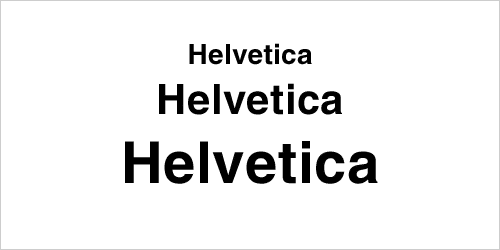
如今,认出 Helvetica 并不需要天才——它无处不在。 平面设计被专业人士和业余设计人员使用——主要是后者。 因为 Helvetica 在个人项目中如此普遍,所以它的声誉略有下降。
您可以将 Helvetica 用于低调的场合(例如演示标题),但如果我们谈论的是徽标或商品,最好选择具有个性的东西。 最重要的是,Helvetica 存在一些间距问题——字母几乎并排放置,这使得视力较弱的人难以阅读。
2. 图拉真
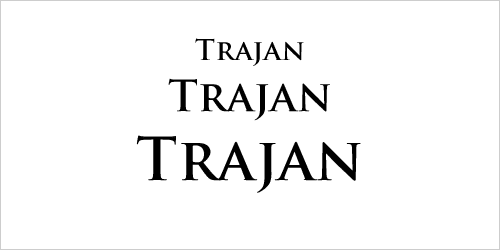
该字体深受好莱坞设计师和插画家的喜爱。 您可能已经在海报或邀请函上看到过它。 它还出现在教育和宗教材料中,部分原因在于其略微奇特的外观。
避免这个的原因之一是它的年龄。 它于 1989 年设计,是最早的专业字体之一,由 Adobe 设计。 该字体的灵感来自罗马建筑,使其非常适合官方场合。
这里还有另一个问题。 在线内容日新月异。 几年前,谷歌和BBC将他们的标志重新设计为简单的无衬线字体。 使用官方字体不再流行——除非场合需要。
3. 加拉蒙德
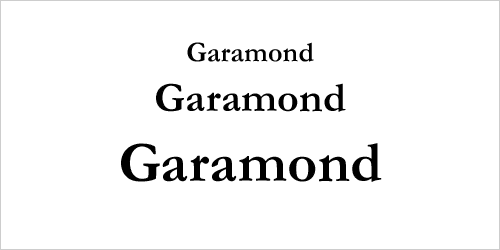
作为最多样化的字体之一,Garamond 产生了多种变体,这极大地解释了它的受欢迎程度。 它的所有修改已经广泛使用了一段时间,但最常见的是 Adobe ITC Garamond。
该字体用于杂志、网站和教科书——它确实是最简单的字体之一,而且可读性很高。 Garamond 对于长篇阅读来说仍然是一个好主意,但是 logos、merch——任何长度小于一个句子的东西——最好是一种更精致的风格。
4.富利
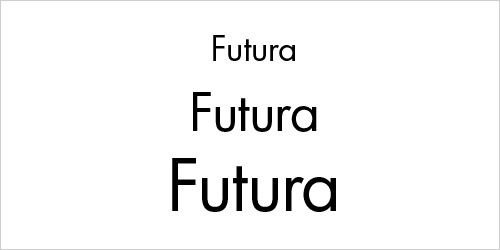
与主要用于大量文本的 Garabond 不同,Futura 更适合用于徽标、标题和书籍封面。 这是令人难忘和大胆的——至少,它是——直到图形设计师充分利用了字体。
现在 Futura 感觉有点多余。 公平地说,用户通常不会注意字体的名称,或者更不会关心将其与特定品牌相关联。 尽管如此,拥有与竞争对手相同字体的机会仍在飙升。 你想在竞争中脱颖而出,而不是直接融入其中。
5. 博多尼
尽管它实际上是最 OG 字体之一,但没有人能否认它仍然是市场上最好的装饰字体之一的事实。 即使对于业余爱好者来说,优势也很明显——窄而优雅的字母带有略微明显的衬线。 与许多衬线字体不同,这款字体既不厚重也不过时,同时仍保持官方氛围。
该字体通常被在其整体风格中使用几何美学的高端品牌所使用。 考虑到如今几何设计的流行程度,难怪 Bodoni 以其明确的形状适合现代营销趋势。
6. Bickham Script Pro
它作为 Vivaldi 最好的替代品之一进入市场——考虑到 Vivaldi 正在缓慢但肯定地成为美国最受鄙视的字体之一,这是一件及时的事情。 它简约但令人难忘——正是您在正式场合所需要的。
尽管有些人认为它是一种你不会因为使用而被解雇的字体,但选择 Bickham Script Pro 并不是最好的主意。 没有石头可以扔在这种字体上——真的是一个很好的字体——但这些年来它无处不在。
7. 果子
作为最受欢迎的标志选项之一,Frutiger 因其轮廓分明、带有轻微曲线的前卫字母而备受喜爱。 它结合了几何老式设计和现代字体中常见的更随意、圆形的方法。
但是,当涉及到徽标时,您不能选择通用字体。 它是您品牌视觉识别的独特部分,因此选择如此广泛使用的东西是让您的品牌迷失的最短途径。 相反,您可以制作自定义字体或在新库中购买独家字体——其中很多看起来比 Frutiger 好得多。
如果您想将其用于较小规模的文本和文本正文,请继续。 Frutiger 是目前最易读的字体之一,读者通常会更好地处理熟悉的字体——因此,您可以提高可读性。
结论
字体设计的经验法则是不惜一切代价避免使用内置 Microsoft Word 中的字体。 使用 Arial 或 Georgia 进行长时间阅读很好,但 Times New Roman 或 Calibri 实在是太多了。
对于非常令人难忘的品牌细节,例如徽标或广告标题,使用这些过度炒作的字体显然是不可行的。 相反,去专业的字体集或开源集——它们通常有很多免费的字体。
另一种解决方案是使用由大公司创建的集合——谷歌或 Adobe 在这里提供帮助。 公司聘请专业设计师,这些合作真正将字体设计提升到一个新的水平。
现在您知道了关键要点——不要为您的关键品牌组件使用最常见的字体。 专业设计师不会滥用过度使用的字体,而是提出独特的创意愿景。